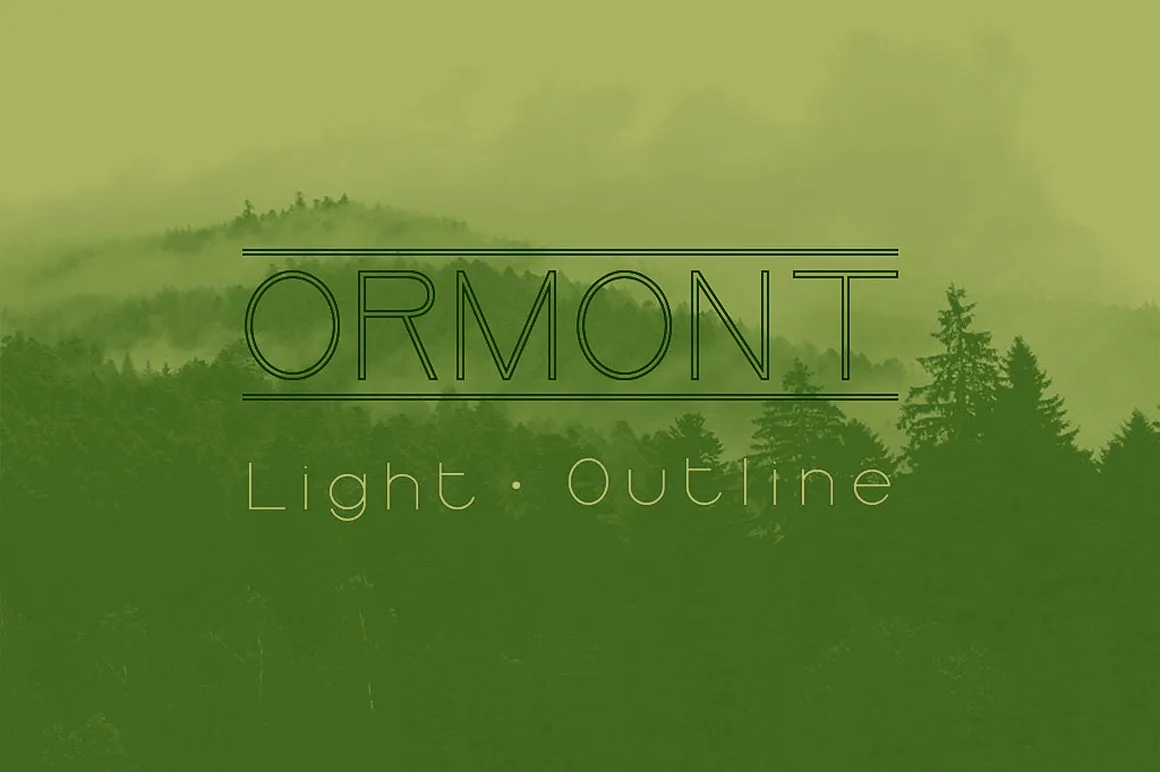
Aqui está uma descrição em português para a página de download da font ‘Ormont Font’, mantendo os requisitos fornecidos: Esta fonte ‘Ormont’ é um estilo elegante e limpo criado por Youssef Habchi, oferecida gratuitamente apenas para uso pessoal. Com seu design simples e moderno, esta fonte ‘sans serif’ traz uma qualidade única à sua produção de texto. O projeto foi concebido pensando em criar um estilo agradável que complementa perfeitamente qualquer tipo de layout digital ou impressão. Para os amantes do desenho gráfico, este design clean e minimalista oferece uma ferramenta versátil para tornar seus projetos ainda mais interessantes e impecáveis. Relembrando, esta descrição é adaptada da fonte ‘Ormont Font’ original em inglês para um tom informativo e convidativo, sem alterar as características fornecidas na descrição original.